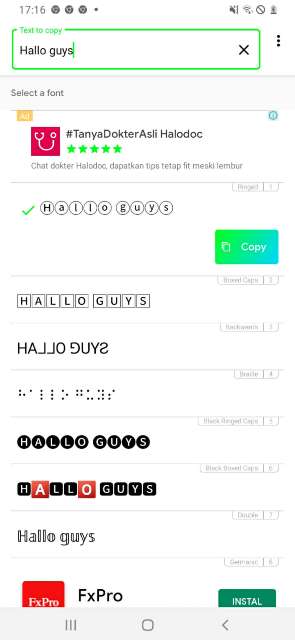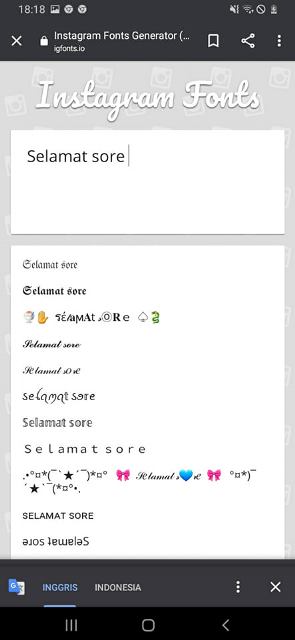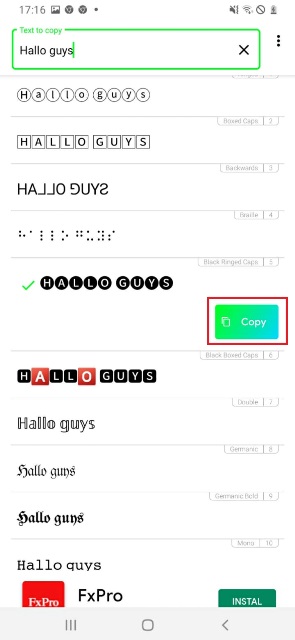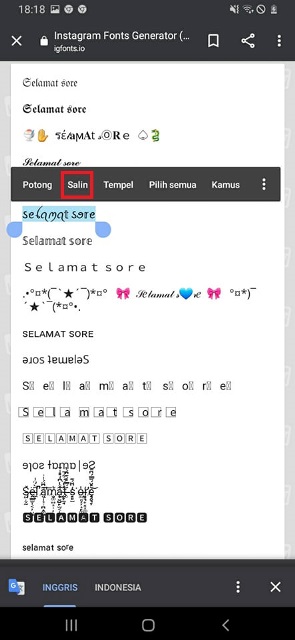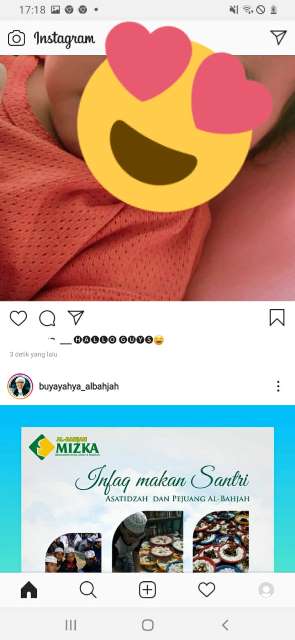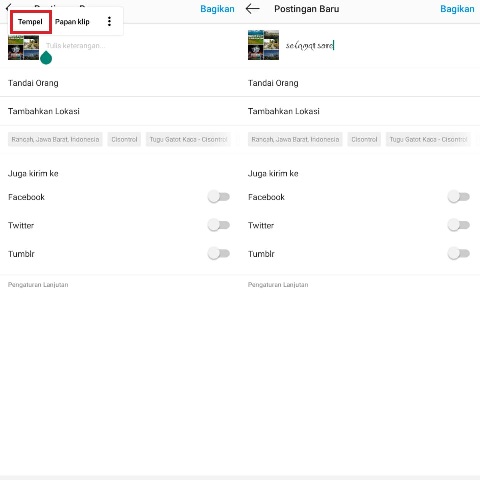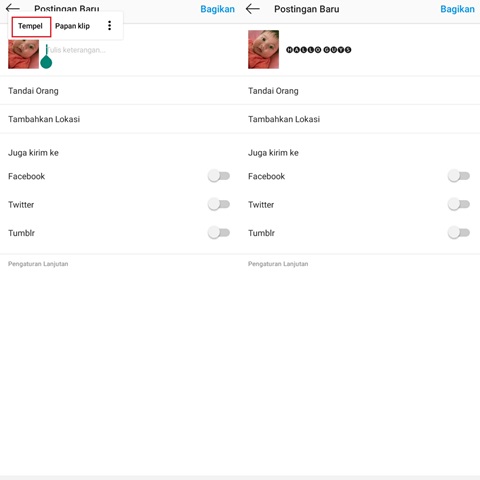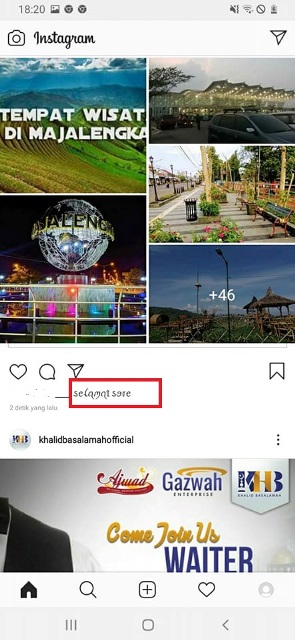
Gampang Banget! Begini Cara Mengganti Font di Instagram yang Kekinian
Gampang Banget Begini Cara Mengganti Font di Instagram yang Kekinian
RANCAH POST – Tau nggak sih kamu sekarang ini sedang tren sekali menggunakan font bold ataupun italic untuk caption Instagram? Nih, ternyata begini cara mengganti font di Instagram yang sangat mudah sekali.
Menuyuguhkan banyak sekali fitur menarik di dalamnya, media sosial Instagram ini memang tengah digemari oleh banyak orang, mulai dari anak remaja sampai orang dewasa.
Setelah baru-baru ini booming filter Augmented Reality (AR) InstaStory, kini para pengguna Instagram kembali dihebohkan dengan munculnya tren style font unik seperti bold ataupun italic.
Bahkan, style tulisan ini juga sempat digunakan oleh beberapa artis dan juga selebgram sehingga menjadikan semua orang merasa penasaran mengenai cara pembuatannya.
Untuk membuat caption dan juga bio di Instagram dengan style ini tidaklah sukit dan tak membutuhkan waktu lama pada saat melakukannya. Penasaran kan gimana cara mengganti font di Instagram agar lebih terlihat menarik? Yuk ikuti cara-cara berikut ini:
Cara Mengganti Font di Instagram
Cara mengubah font Instagram dengan aplikasi
Cara yang pertama bisa kamu lakukan yakni kamu harus mengandalkan sebuah aplikasi ya, guys. Dengan menggunakan aplikasi ini, kamu tak hanya mendapatkan tulisan miring, namun juga style lainnya seperti bold.
Nah, untuk caranya sendiri, berikut ini langkah-langkah yang bisa kamu lakukan.
• Pertama-tama download terlebih dahulu aplikasi text generator. Contohnya saja aplikasi text generator bernama Fontify.
• Jika proses pengunduhan telah selesai, kemudian kamu buka aplikasinya.
• Selanjutnya, tuliskan kata-kata yang akan kamu ubah jenis style font-nya.
• Maka hasilnya akan langsung muncul di bagian bawah. Di tahap ini kamu harus memilih style font yang kamu inginkan.
Cara mengganti font Ig
• Jika sudah, maka cara mengganti font di Instagram selanjutnya yakni dengan memilih jenis font yang akan kamu gunakan.
• Selanjutnya pilih font tersebut dan tekan tombol Copy.
Cara mengubah font Instagram
• Jika sudah, kamu buka aplikasi Instagram dan upload feed Instagram yang menarik.
• Pada tahap menulis caption, kamu hanya tinggal menempel atau paste tulisan yang sebelumnya sudah disalin. Caranya, sentuh dan tahan hingga muncul opsi Paste.
Tips mengganti font unik di Ig
• Jika sudah, kamu pilih tombol Share untuk membagikan postingan.
Langkah langkah mengganti font Instagram
Tak hanya style font bold atau italic saja, namun ada juga jenis font keren lainnya yang juga bisa kamu gunakan pada aplikasi ini.
Tak hanya akan menjadikan tulisan aesthetic di caption, namun cara mengganti font di Instagram ini pun tentunya akan mempecantik bio kamu di Instagram.
Cara mengubah font Instagram tanpa aplikasi
Jika sebelumnya menjelaskan bagaimana cara mengubah font Instgram menggunakan aplikasi, maka kali ini kamu bisa melakukannya tanpa harus menginstall aplikasi apa pun.
Untuk cara mengubah font IG tanpa aplikasi, kamu bisa melakukan langkah-langkah berikut ini:
• Pertama, kamu kunjungi terlebih dahulu salah satu situs text generator yang bisa mengubah style font sesuai dengan yang kamu inginkan.
• Kamu bisa mengunjungi situs Instagram Fonts di URL https://igfonts.io/.
• Setelah itu, kamu tulis kata-kata yang akan kamu ubah style font-nya menjadi tebal, miring, atau yang lainnya di kolom yang telah disediakan.
• Jika sudah, maka hasilnya akan langsung muncul seperti di bawah ini ya, guys. Di tahap ini, kamu bisa mencari style font sesuai dengan selera yang kamu inginkan.
Cara mengganti font pada Instagram
• Cara mengganti font di Instagram berikutnya ialah kamu copy font tulisan yang diinginkan dengan cara menyentuh dan menahan pada bagian tulisan tersebut. Kemudian pilih tombol Copy.
Cara mengubah font pada IG
• Selanjutnya, buka aplikasi Instagram dan buat postingan feed terbaru.
• Di tahapan menulis caption, tempel atau paste tulisan yang sebelumnya telah kamu Copy hingga muncul tombol Paste.